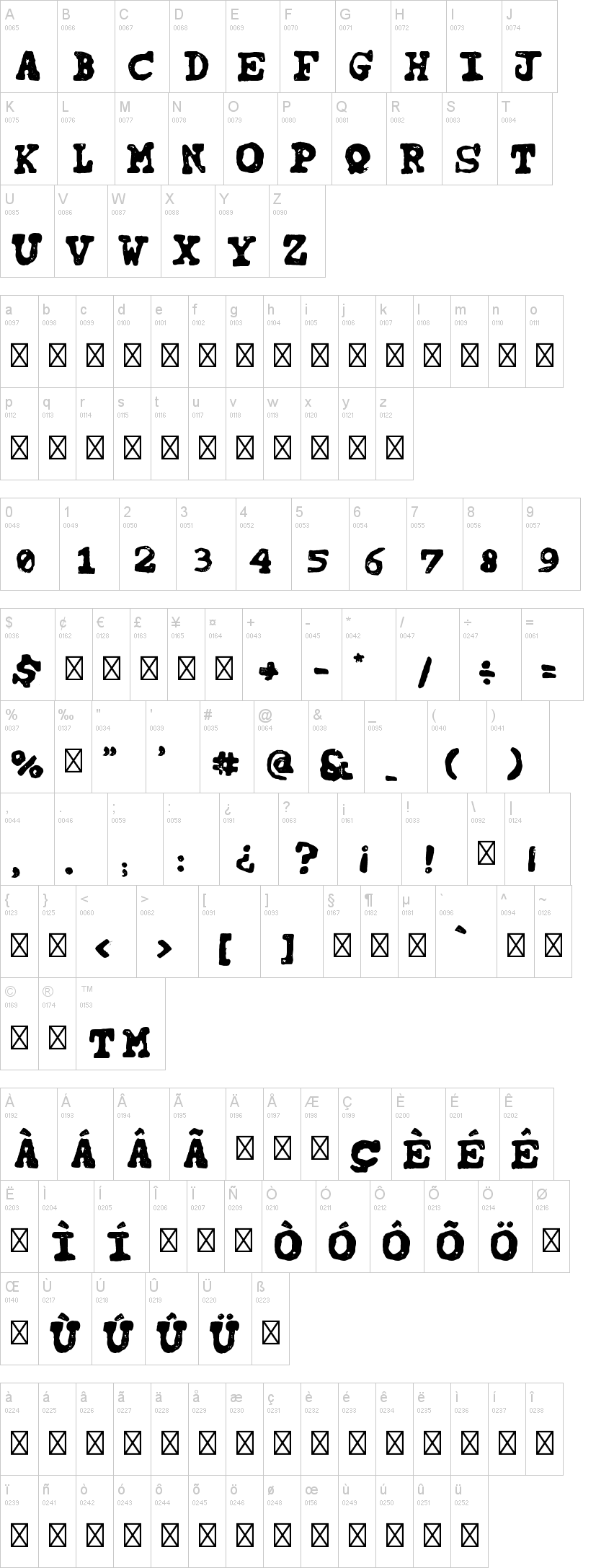
tipocarimbado-Light.otfNote of the authorTipografia desenvolvida à partir da digitalização de impressões de carimbos. Os carimbos foram gravados à mão em matrizes de linóleo de 3mmX3mm.